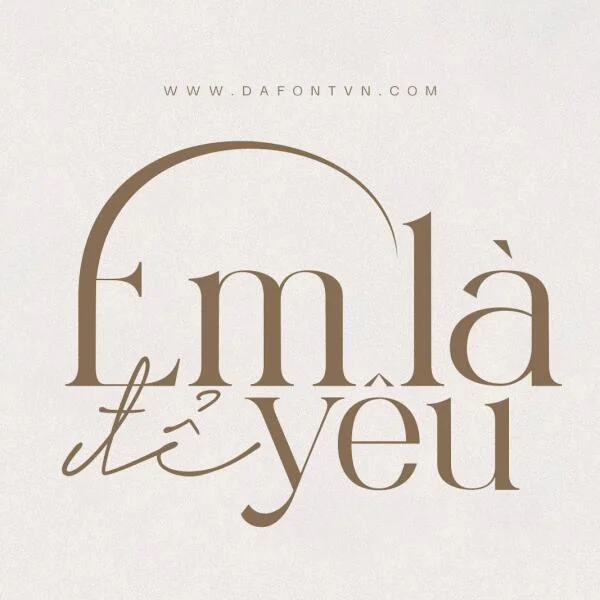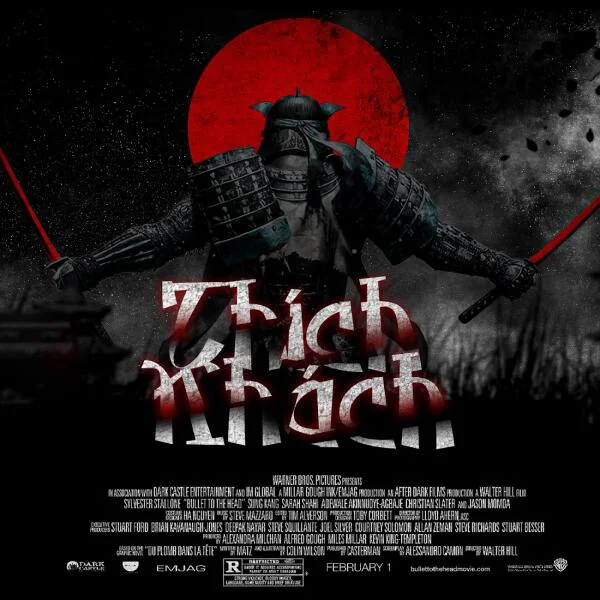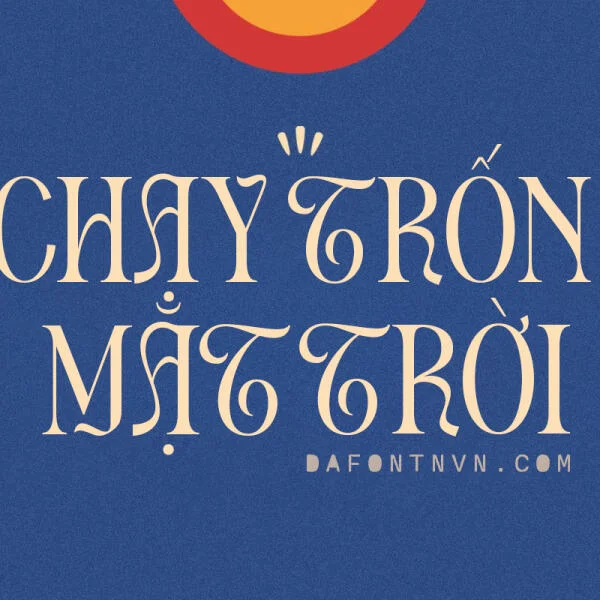
Tổng quan về Font Sinistre
Font việt hóa Sinistre (Sinistre S† Caroline) một kiểu font mang phong cách gothic với các nét chữ lấy cảm hứng từ những thiết kế thời Phục hưng tuy nhiên đây lại là một phông chữ khá hiện đại phù hợp cho rất nhiều các thiết kế khác nhau như thời trang, poster, thiệp, typography, bìa sách, bao bì,...
Font Việt Hóa Sinistre - Sinistre S† Caroline
Mẫu 1
Font Sinistre việt hóa
Mẫu 2
Sinistre S† Caroline Font
Mẫu 3
Chi tiết ký tự của Font Việt hóa Sinistre
Sinistre Font Character
Chi tiết ký tự